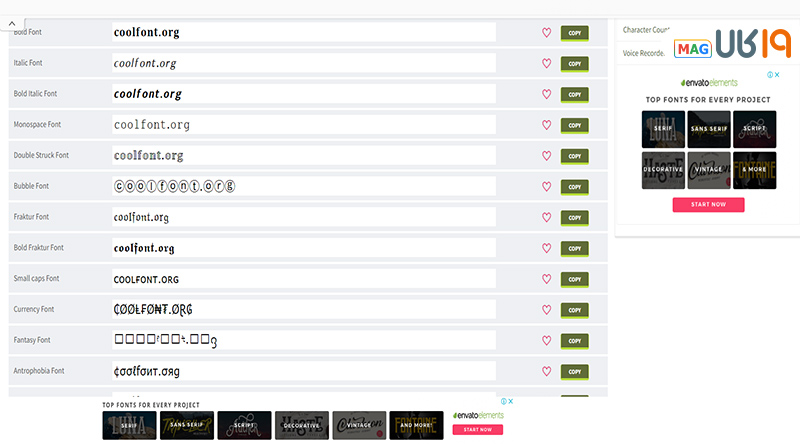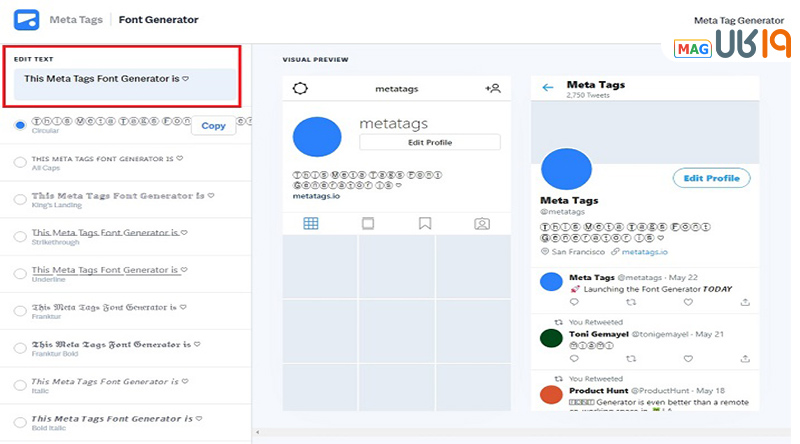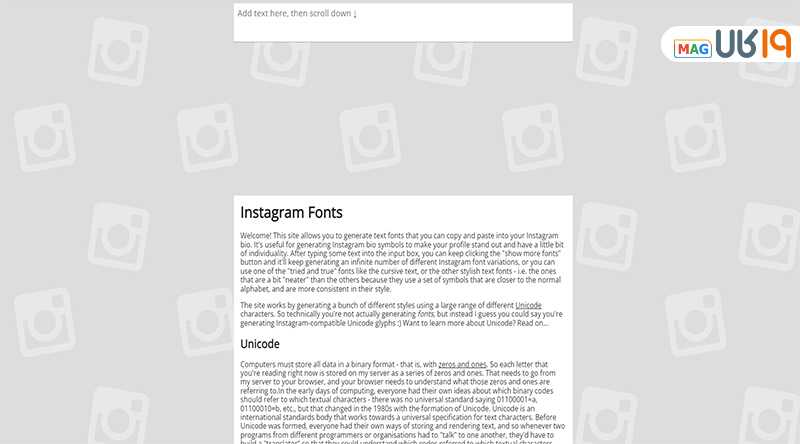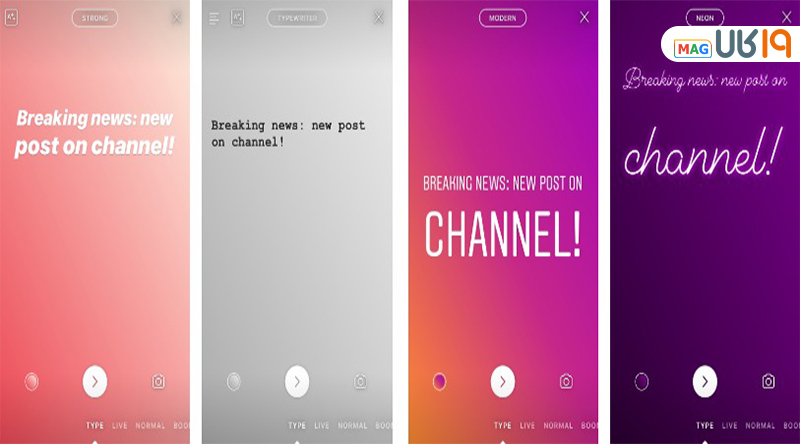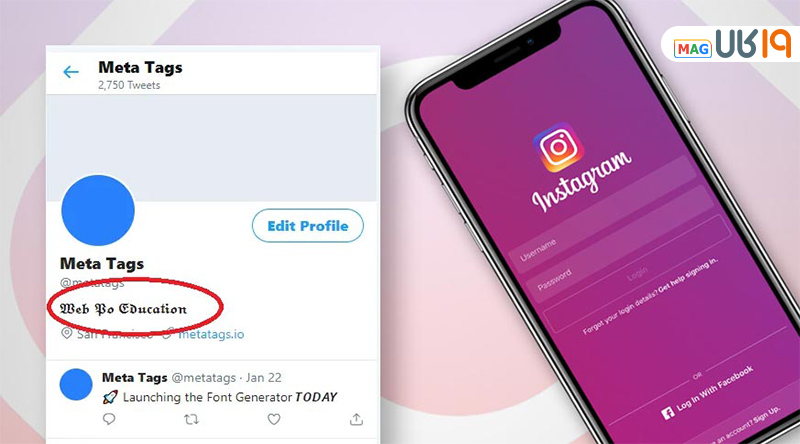
تغییر فونت اینستاگرام در بیو و استوری (انگلیسی و فارسی)
فونت اینستاگرام را چگونه تغییر دهیم؟ اگر اهل استوری گذاشتن، نوشتن کپشنهای طولانی یا ساختن یک بیوی جذاب هستید، احتمالاً شما هم حداقل یکبار این سوال برایتان پیش آمده که بقیه چطور از این همه فونت خاص و متفاوت برای بیو و استوری اینستاگرام استفاده میکنند. واقعیت این است که خود اینستاگرام فقط چند فونت محدود در استوری و بخشهای مختلف دارد، اما با کمک ترفندها، سایتها و برنامههای جانبی، میتوان هم برای متنهای فارسی و هم انگلیسی، استایلهای جذابتری ساخت و مستقیم در بیو، اسم، استوری و حتی کپشن استفاده کرد.
از آنجایی که این مقاله چند سالی است روی سایت قرار دارد و اینستاگرام هم مدام در حال آپدیت شدن است، در این نسخه جدید، تمام روشها را بهروز کردیم؛ هم برای کاربرانی که بهدنبال فونت انگلیسی برای بیو اینستاگرام هستند، و هم برای کسانی که میخواهند فونت فارسی برای بیو اینستاگرام در اندروید و iOS داشته باشند. کافیست قدمبهقدم آموزشها را دنبال کنید، متن دلخواهتان را بسازید، کپی کنید و در اینستاگرام بچسبانید (Paste کنید).
تغییر فونت اینستاگرام یعنی چه؟
وقتی میگوییم تغییر فونت اینستاگرام منظورمان این نیست که فونت داخلی برنامه را مثل تنظیمات فونت ویندوز یا اندروید عوض کنیم؛ این کار در خود اپ اینستاگرام ممکن نیست. کاری که انجام میدهیم در واقع استفاده از حروف و کاراکترهای یونیکد و فونتهای آماده در سایتها و برنامههاست. این ابزارها متن معمولی شما را به شکلهای مختلف (بولد، ایتالیک، حروف دوترا ضرب، حروف فانتزی، حروف ترکیبی و…) تبدیل میکنند و شما فقط کافی است آن را کپی و در اینستاگرام پیست کنید.
این روش برای همه جا کار میکند؛ یعنی میتوانید فونت اسم، بیو، هایلایتها، کپشن پست و حتی کامنتها را با همین ترفند تغییر دهید. برای متنهای فارسی هم چند راهحل وجود دارد؛ از ترفندهای ساده برای فاصلهگذاری و زیباتر شدن خط، تا استفاده از برنامههایی که فونتهایی مثل نستعلیق، ایرانسنس، لالهزار و… را روی عکس و استوری پیاده میکنند.
مزایای تغییر فونت برای اینستاگرام چیست؟
اولین و مهمترین دلیل استفاده از فونتهای جدید اینستاگرام این است که کمک میکنند وسط این همه پیج شبیهبههم، صفحه شما دیده شود. یک بیوی کوتاه، اما با فونت خاص و تمیز، خیلی بیشتر از یک متن شلوغ و معمولی در ذهن کاربر میماند. همین موضوع برای استوری، کپشن و حتی اسم پیج هم صدق میکند.
- افزایش جذابیت بصری: فونت خاص برای بیو، استوری و کپشن، در نگاه اول نظر کاربر را جلب میکند و باعث میشود بیشتر روی پروفایل شما وقت بگذراند.
- برندسازی شخصی یا تجاری: اگر مداوم از یک سبک فونت مشخص استفاده کنید، بهنوعی برای خودتان «امضا» میسازید و به مرور، همان فونت یادآور پیج شما میشود.
- نمایش خلاقیت: استفاده درست از فونتهای خلاقانه (بدون افراط) حس حرفهای بودن و توجه به جزئیات را به مخاطب منتقل میکند.
- هماهنگی با زبان فارسی و انگلیسی: میتوانید برای بیو فارسی و انگلیسی، استایلهای جداگانه انتخاب کنید و بخشهای مهم مثل نام برند، آیدی یا هشتگها را با فونت متمایز نمایش دهید.
فقط فراموش نکنید که زیادهروی در استفاده از فونتهای عجیب و ناخوانا، نتیجه برعکس میدهد و ممکن است کاربر را خسته یا سردرگم کند. در ادامه چند روش استاندارد، ساده و امن برای تغییر فونت اینستاگرام در بیو و استوری (انگلیسی و فارسی) معرفی میکنیم.
آموزش تغییر فونت بیو اینستاگرام (فارسی و انگلیسی)
بیو اینستاگرام اولین جاییست که کاربر بعد از ورود به پروفایل شما میبیند؛ پس طبیعی است که «فونت بیو اینستاگرام» نقش مهمی در جلب توجه و حرفهای دیده شدن پیج داشته باشد. برای تغییر فونت در بیو، سه روش کلی داریم: استفاده از سایتهای آنلاین، استفاده از ترفندهای مخصوص متن فارسی و استفاده از برنامهها یا کیبوردهایی که فونت آماده ارائه میدهند.
فونت انگلیسی برای بیو اینستاگرام (آنلاین و بدون نصب برنامه)
اگر بیشتر متن بیوی شما انگلیسی است و دنبال فونت انگلیسی برای بیو اینستاگرام هستید، سادهترین و امنترین راه استفاده از سایتهای تغییر فونت اینستاگرام است. این سایتها متن معمولی شما را به شکلهای مختلف (Bold، Italic، فانتزی، مینیمال و…) تبدیل میکنند و فقط کافیست متن نهایی را کپی و در اینستا پیست کنید.
مراحل کلی کار تقریباً در همه سایتها یکسان است:
- یکی از سایتهای سایت تغییر فونت اینستاگرام مثل IGfonts، MetaTags Font Generator یا CoolFont را در مرورگر باز کنید.
- در باکس اول، متن بیو یا اسم خود را (به انگلیسی) بنویسید؛ مثلاً: Digital Creator | Tech Lover.
- لیستی از استایلها و فونتهای انگلیسی برای اینستاگرام در پایین یا کنار صفحه ظاهر میشود؛ چند مدل را اسکرول کنید و خواناترین گزینه را انتخاب کنید.
- روی فونت مورد نظر ضربه بزنید تا متن انتخاب شود، آن را Copy کنید.
- وارد اینستاگرام شوید، به بخش Edit Profile > Bio بروید، متن کپیشده را Paste کنید و در نهایت Save را بزنید.
برای اسم پیج، کپشن یا حتی کامنتها هم همین روال جواب میدهد. فقط دقت کنید فونتی که انتخاب میکنید بیش از حد شلوغ و ناخوانا نباشد؛ چون در صفحههای کوچک موبایل، خوانایی مهمتر از فانتزی بودن است.
فونت فارسی برای بیو اینستاگرام در اندروید
برای بعضی کاربرها فقط فونت انگلیسی برای بیو کافی نیست و میخواهند متن بیو را کامل فارسی بنویسند. خود اینستاگرام امکان نصب فونت فارسی جدید ندارد، اما چند ترفند ساده برای ساخت فونت فارسی برای بیو اینستاگرام اندروید وجود دارد.
میخواستم بپرسم فونت نستعلیق آنلاین قابل کپی برای اینستاگرام هم داریم؟
ممنون میشم راهنمایی بفرمایید.